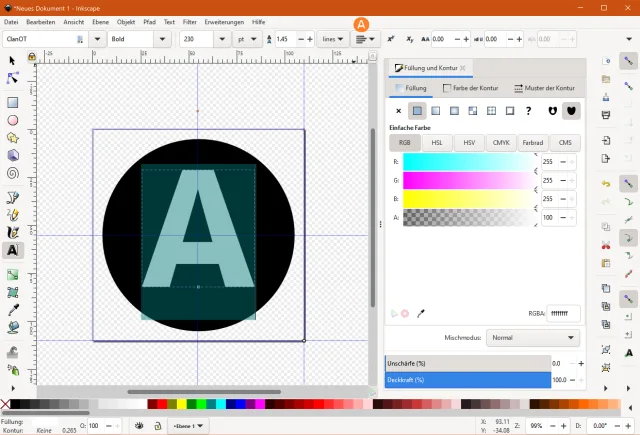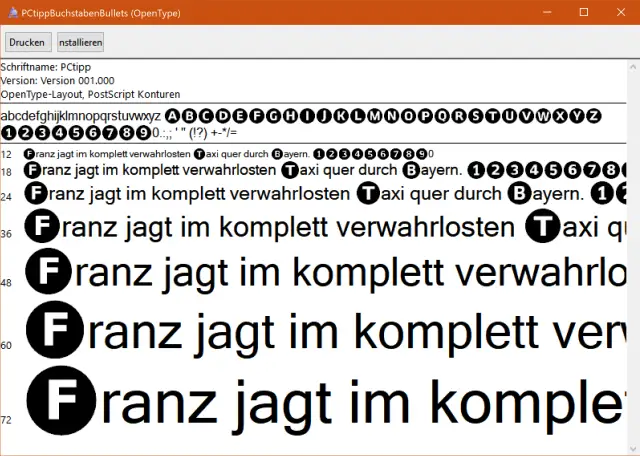
Einen benutzerdefinierten Font erstellen
Haben Sie bestimmte Symbole, die Sie eigentlich häufig bräuchten, aber so, wie Sie diese haben wollen, in keiner Schriftart finden? Dann erstellen Sie Ihren eigenen Font.
Wenn es den Font Ihrer Wünsche nicht gibt, erstellen Sie ihn einfach selbst
Wingdings hat nur Ziffern in Kreisen, aber keine Buchstaben
Der Autorin wurde es mit der Zeit zu mühsam, in die online verwendeten Screenshots Kreisli zu zeichnen, bloss, um darin Buchstaben zu platzieren. Denn es kommt nicht selten vor, dass wir in Texten auf eine «Markierung A» im «Bild X» hinweisen. Warum gibts diese «Kreisbuchstaben» nicht gleich in einem Font? Schliesslich gibts etwa in der Windows-Schriftart «Wingdings» zumindest die Ziffern – sogar wahlweise in gefüllten oder leeren Kreisen, Bild 1 (A). Je nach Bildbearbeitung lassen sich solche Elemente zwar einmal kreieren und zur Wiederverwendung in eine Bibliothek stecken. So machen wir es schliesslich auch im gedruckten Heft, für welches wir in Adobe InDesign die Buchstaben aus einer Bibliothek ziehen können. Aber die Autorin verwendet mal diese, mal jene Software. Und nicht in jeder ist das mit den Bibliotheken überhaupt machbar.
Wie wärs mit einem eigenen Font?
Ein zentral in Ihrem Betriebssystem (Windows, Linux, Mac) installierter Font lässt sich in jeder Anwendung benutzen, die eine Schriftartauswahl bietet. Seine Buchstaben oder sonstigen Zeichen lassen sich genau wie bei anderen Schriftarten problemlos mit anderen Farben versehen. Und sie lassen sich – weil die Buchstaben als SVG-Dateien erstellt werden – quasi endlos skalieren, ohne Treppeneffekte zu zeigen, falls Sie die Zeichen mal etwas grösser darstellen wollen.
Es gibt etwas Arbeit, aber ist nicht allzu schwierig und mit Open-Source-Software zu machen. Wenn Sie sich selbst an ein solches Experiment wagen wollen, bedenken Sie einige Punkte, siehe Folgeseite.
Wichtige Hinweise & Vorbereitung
Wichtige Hinweise
Typografie ist eine Wissenschaft für sich. Einen professionellen, alle typografischen Anforderung erfüllenden Font, der sich als richtige Schreibschrift benutzen lässt, werden Sie mit den nachfolgenden Tipps nicht erzeugen. Aber falls Sie zum Beispiel in der Firma, für Hobby oder im Verein häufig eine ganze Reihe von speziellen Symbolen brauchen, die Sie in allen Anwendungen benutzen können und in keinem bestehenden Font finden, dann eignet sich das Vorgehen durchaus.
Vorbereitung
Buchstaben basteln
Sie können mit den Zeichenwerkzeugen in InkScape natürlich allerlei andere Formen erstellen. Beachten Sie einfach, dass Sie fürs Vorbereiten der Buchstaben nur Schwarz verwenden, allenfalls zusammen mit Weiss, damit Sie Teile einer Form «wegstanzen» können. Das mit dem herausstanzen benutzen wir hier auch. Angenommen, Sie wollen ebenfalls Ziffern und Buchstaben in einem ausgefüllten Kreis haben.
Starten Sie InkScape. Via Datei/Dokumenteinstellungen ändern Sie die Seitengrösse, zum Beispiel auf 110×110 Millimeter. Bei «Hintergrund» aktivieren Sie Schachbrettmuster als Hintergrund, damit man die Transparenz sieht. Es empfiehlt sich, via Bearbeiten zu Hilfslinien an Seitenrändern erstellen zu greifen. Ziehen Sie je eine horizontale und eine vertikale Hilfslinie exakt in die Mitte des Dokuments.
Jetzt der Kreis: Klicken Sie aufs Zeichenelement Kreis und malen Sie einen ungefähren Kreis. Klicken Sie nun in der linken Symbolleiste oben aufs Pfeilsymbol und klicken Sie den Kreis an. Oben sehen Sie nun die Werte: X für den Abstand zum linken Rand, Y für den Abstand vom oberen Rand, B für die Breite des Kreises und H für dessen Höhe. Wir wählen für Breite und Höhe je 100 Millimeter und für den Abstand von oben und von links je 5 Millimeter. Klicken Sie mit Rechts darauf und öffnen Sie Füllung und Kontur. Gestalten Sie die Buchstaben ausschliesslich mit Schwarz. Was weiss werden soll, muss transparent werden. Daher wählen wir bei Füllung das Kästchen für Einfache Farbe. Sie können die Farben unten auswählen. Alternativ können Sie auch Farbcodes ins RGBA-Feld eintragen. Schwarz mit 100% Deckkraft ist 000000ff.